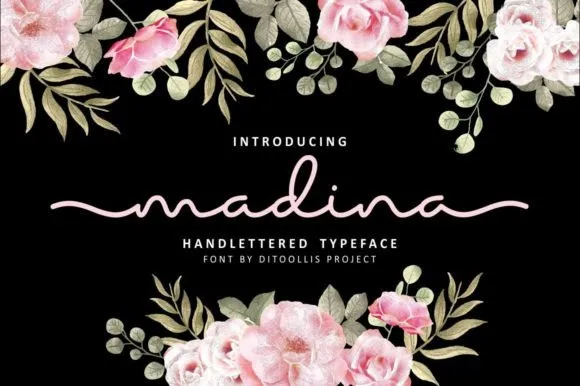
Madina Handlettered Font – Download Grátis
Bem-vindo à categoria das fóntes Script! Hoje temos agradecemos apresentar a vocês Madina Handlettered Font. Esta novidade traz uma assinatura de letra cheia e handmade, com um estilo elegante e natural. Madina é uma fonte de script que se destaca por seu charme pessoal e sofisticação. Ela oferece uma aparência casual mas elegante, ideal para criar cartões de agradecimento encantadores, arte de cartão de visita impressionantes, postagens de mídia social chamativas e até cartas de amor engraçadas. Seus traços naturais são perfeitos para muitos projetos, desde logotipos e marcas, cartões de convite e decoração escrita, design de casamento, postagens nas redes sociais, anúncios, embalagens de produtos, cartazes, designs de produto, etiquetas, fotografia, marca d’água, eventos especiais ou qualquer outra coisa. Além disso, sua elegância faz uma ótima combinação com frases e moda. Se você está buscando uma fonte para um projeto que exalte seu estilo pessoal, Madina é uma escolha brilhante. Vamos conferir como ela dará vida ao seu próximo trabalho?